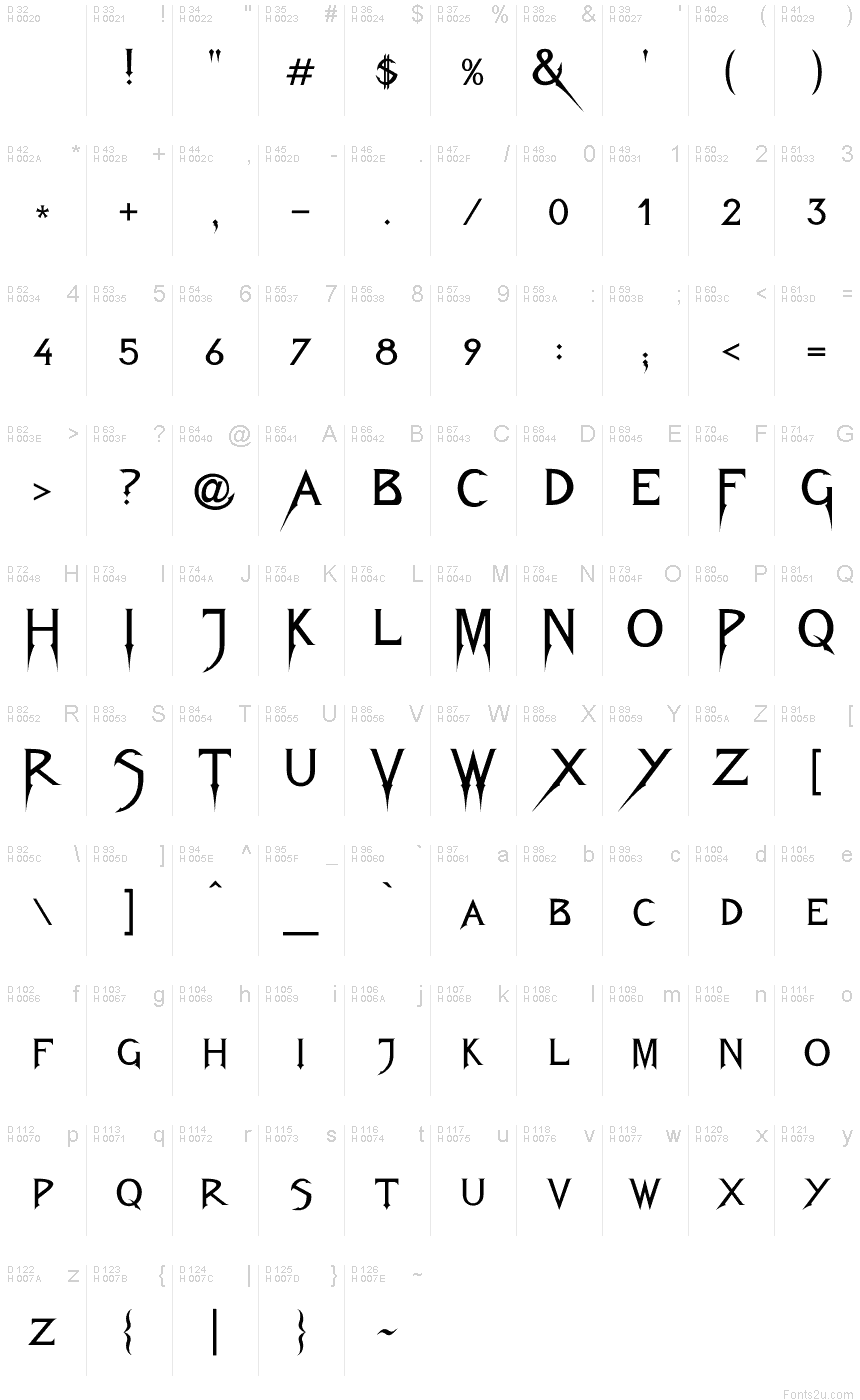
Fiolex Mephisto je moderní gotické písmo typu display, které je k dispozici jako bezplatné a zaujme svým teatrálním a vysoce kontrastním vzhledem. Písmena v sobě snoubí drama černošvabachu (blackletter) s módní ostrostí; široké, masivní tahy doplňují jemné křivky a jehlové špičky, které velkým písmenům dodávají lehce zlověstnou eleganci.
Písmo se skvěle hodí na titulky plakátů, obaly alb, balení v žánru „dark romance“, eventové letáky i redakční nadpisy, kde krátký text vyžaduje mix přísnosti a půvabu. Jako bezplatný font je ideální i pro monogramy a titulní karty, protože díky špičatým detailům a výraznému kontrastu působí i pár písmen dojmem nabitého emblému.
Obsahuje astrologické, tarotové a další mýtické symboly.
Fiolex Mephisto
Fiolex Software
Includes Astrology, Tarot and other mythical symbols (use the Windows Character Map to insert them).